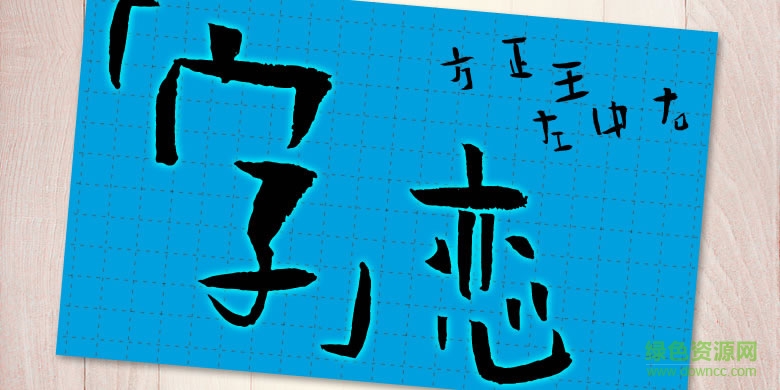
方正王左中右体是一款方正字体出品的简体字体,乍看之下有些奇怪但是当你用全局的眼光来审视时,又发现这款字体有种莫名的平衡感,实在很有趣味。欢迎大家来绿色资源网下载!
写字大致有两个方向,一个是追求局部笔画的笔锋和形状,一个是追求整体汉字的结构和布局。方正王左中右体追求的是后者。 具体而言,就是打破每个字最普遍最让大家眼熟的结构和布局,放大不该放大的,缩小不该缩小的,拉长不该拉长的,拓宽不该拓宽的,不该空的地方空,不该破的地方破,让每一个笔画似乎都失控,让整个字的重心都转移,但最终却形成新的平衡。字还是那个字,只是增减挂钩了。 创作过程与其说是在写字,不如说是在画画,在拼图,把“老字”的笔画一个个拆散,变形,再重新拼成一个歪瓜裂枣的“新字”。 如果用形容词描述这个字体的话,可能下面三个字可能会比较接近:拙,顽,懒。